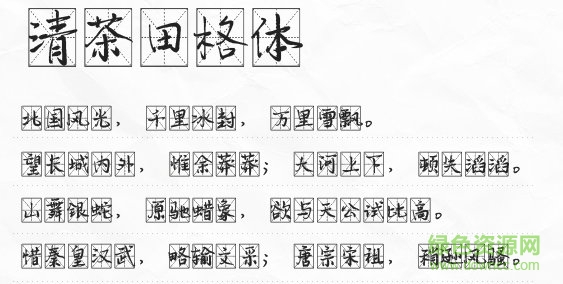
清茶田格體是一款極具古風(fēng)韻味的兒童藝術(shù)字體,加入了田字格的裝飾,給文字童真可愛的活潑趣味,字跡飄逸而清揚(yáng),喜歡的朋友就來綠色資源網(wǎng)下載收藏吧!
清茶田格體字跡如茶,給人淡泊灑脫之態(tài),田字格的修飾,使其在形象上近似于書帖臨摹的范本,采用鋼筆書法的設(shè)計讓文字更顯端正沉穩(wěn)。
而清茶田格體能快速制作田字格范本,讓你的平面設(shè)計更加簡便、自然。